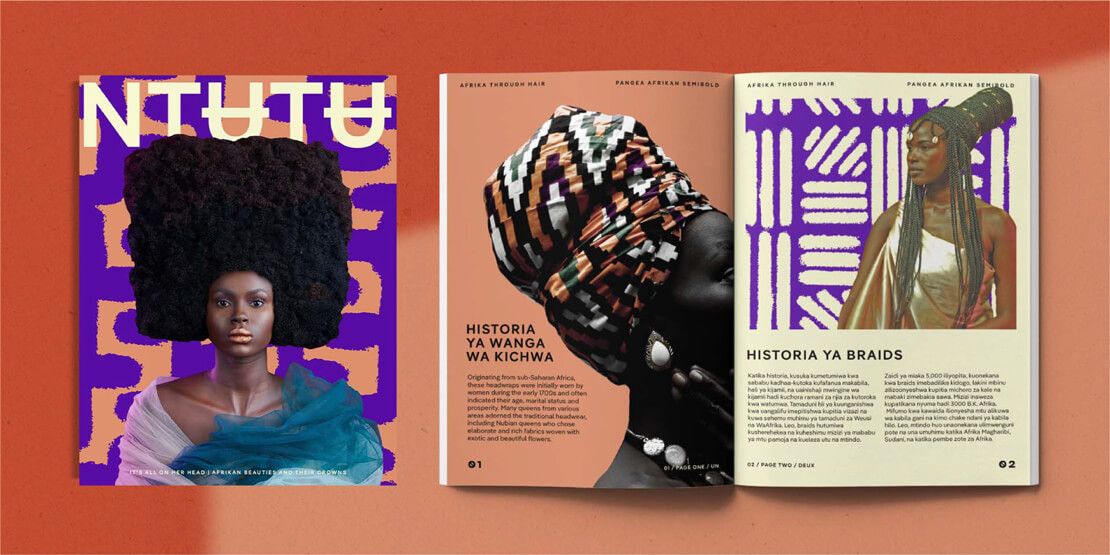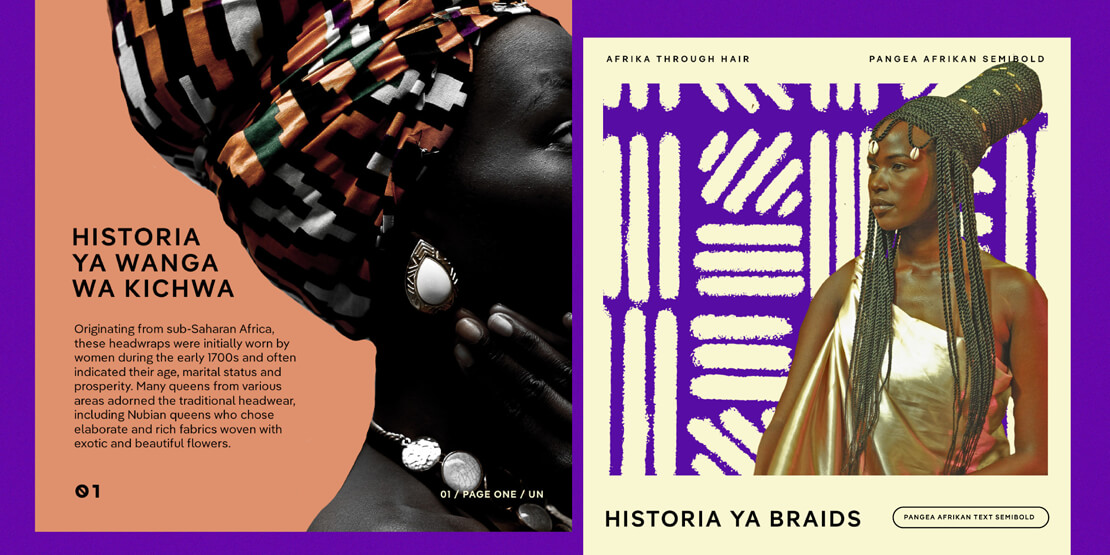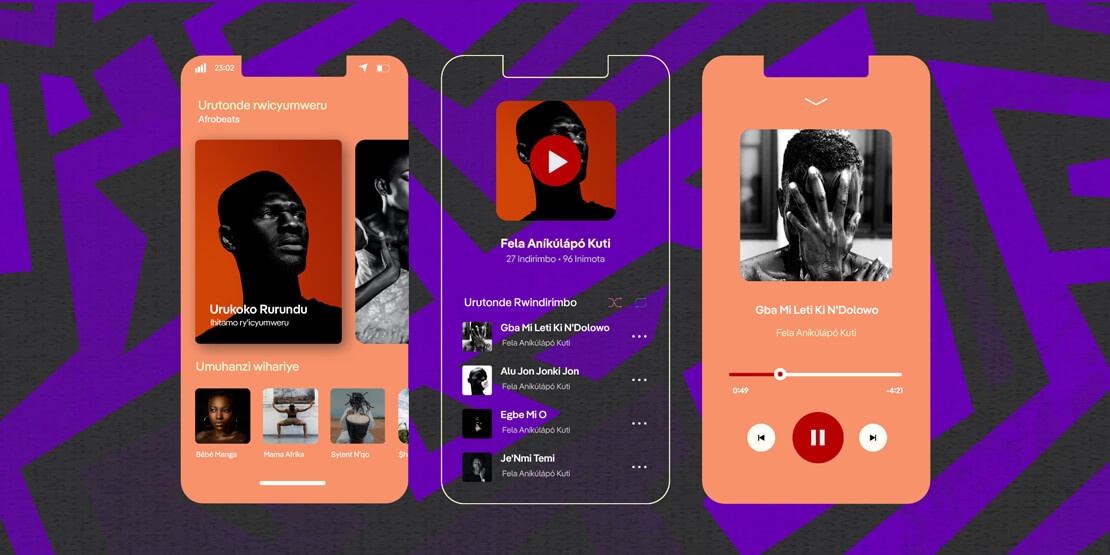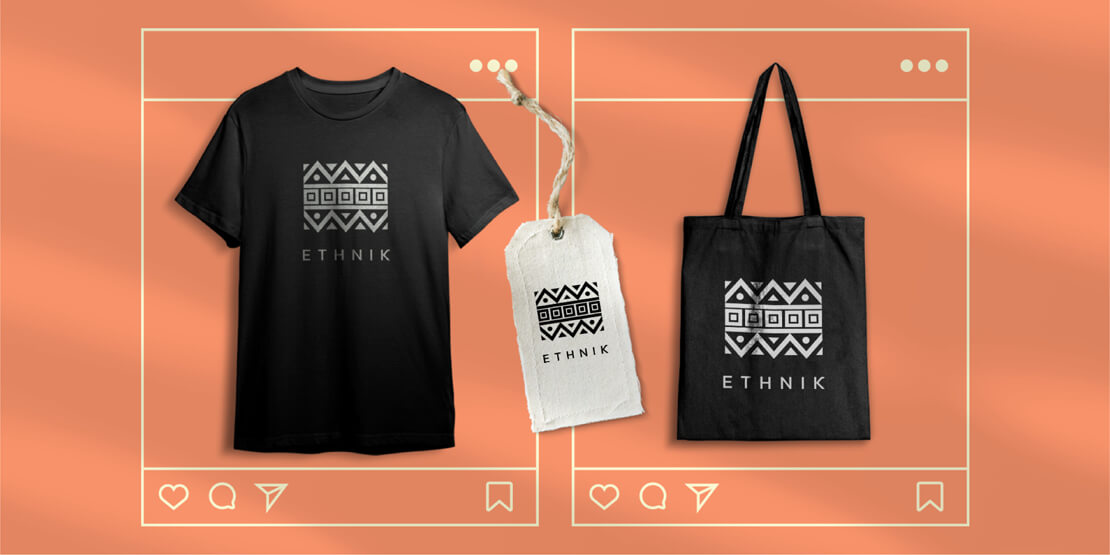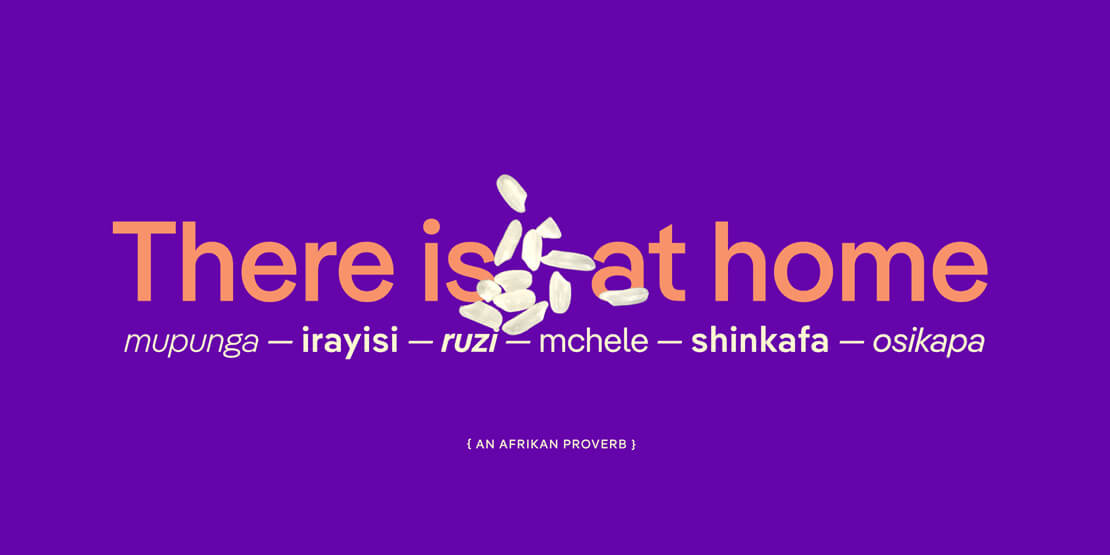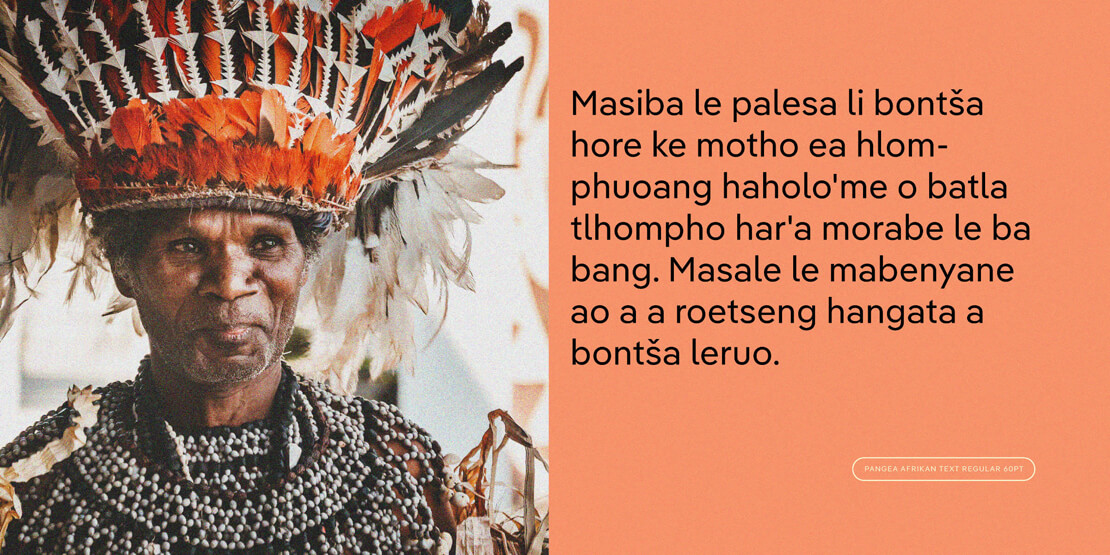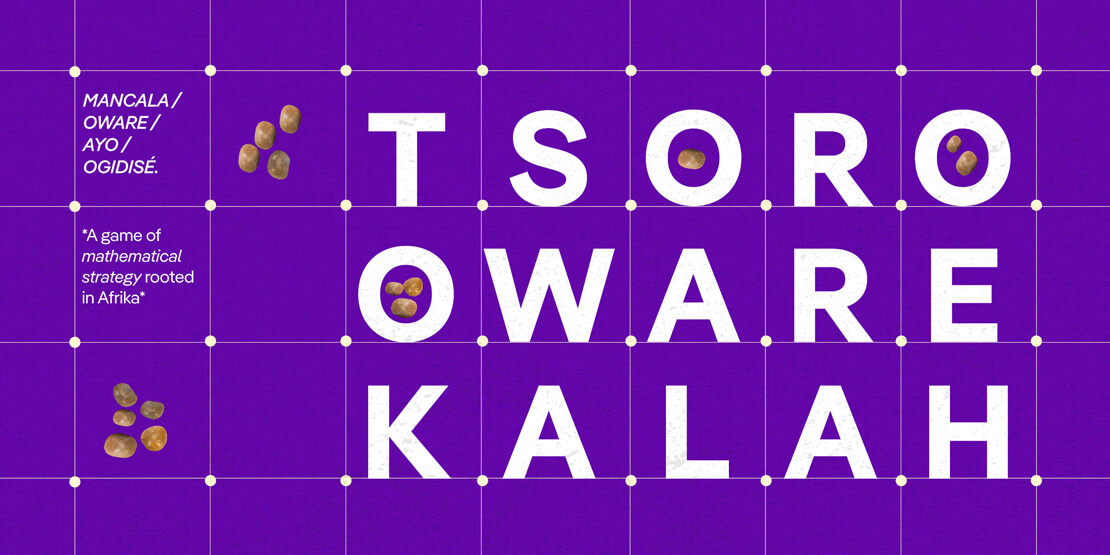
Pangea Afrikan: Kostenlose Unterfamilie von »Pangea«
Mit »Pangea Afrikan« stellen Designer Christoph Koeberlin und der Schriftenanbieter Fontwerk eine kostenlose Unterfamilie von »Pangea« vor. Diese soll alle lateinischen afrikanischen und indigenen Sprachen unterstützen.
Neben dem Bestreben, einen Beitrag zum Klimaschutz zu leisten, sollen mit den Schriften zudem auch Kulturen und Kontinente verbunden werden. Gelingen soll dies unter anderem durch die Förderung unterrepräsentierter Sprachen.
Erfolgreiche Schriften repräsentieren üblicherweise nur die Alphabete Europas und Amerikas. Mit der Unterfamilie kommen zusätzliche Zeichen für lateinische afrikanische Sprachen wie Hausa, Yoruba, Igbo, Lingala, Mende oder Umbundu oder auch einige indigene nord-amerikanische wie Lushootseed oder Navajo hinzu.
Stilistisch bleibt der Sprachausbau der Formel treu und überträgt die platzsparende Kompaktheit enger Groteskschriften auf eine schnörkellose geometrische Serifenlose. Für Flexibilität sorgen die beiden optischen Größen »Pangea Afrikan« und »Pangea Afrikan Text«.
Das vorliegende Sprachupdate bedeutet noch nicht das Ende der Bemühungen um den afrikanischen Kontinent, schließlich beinhaltet es zunächst die entsprechenden lateinischen Sprachen. Gemeinsam mit nativen Designerinnen und Designern sollen weitere Alphabete wie N’Ko oder Ge’ez ergänzt werden. Auch diese werden dann kostenfrei zur Verfügung gestellt.